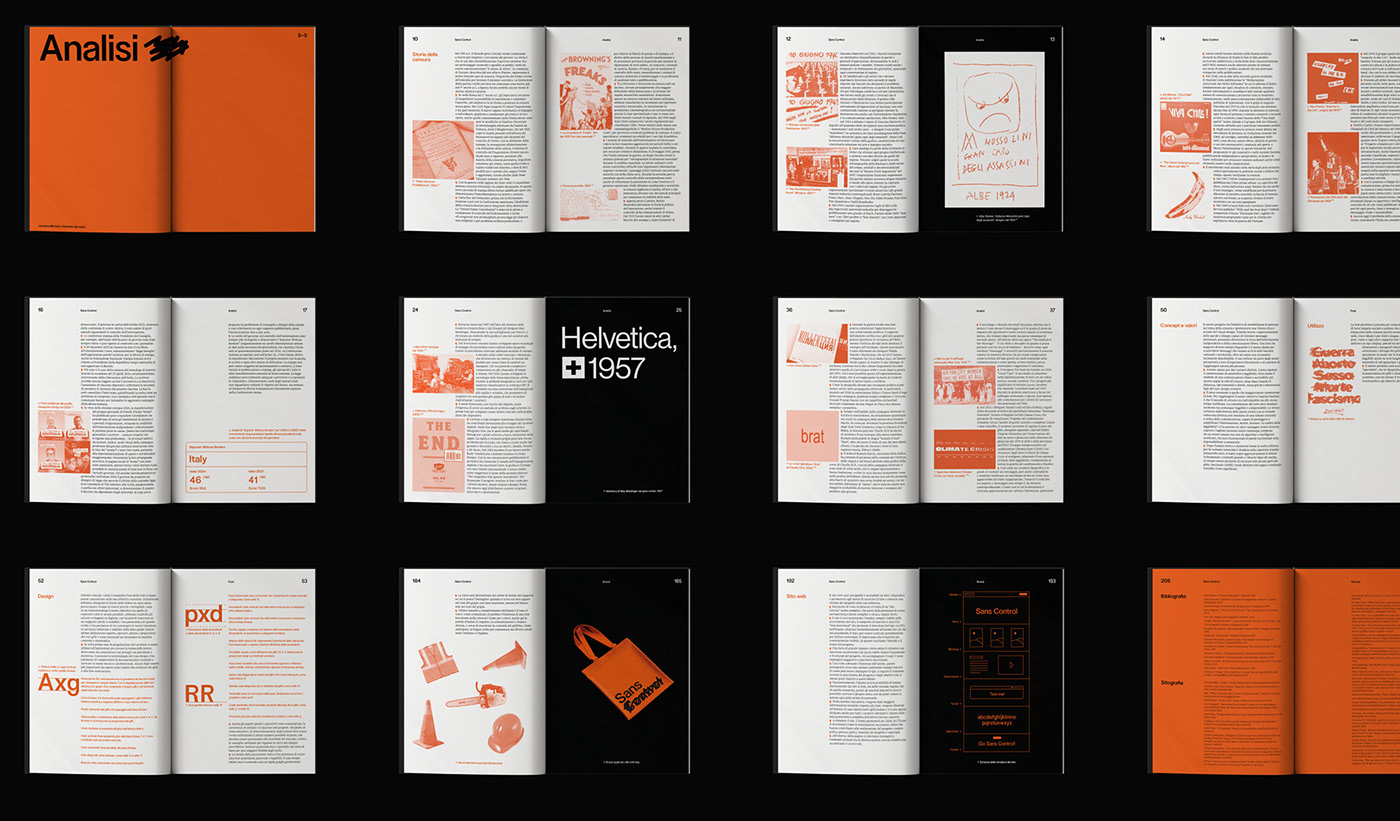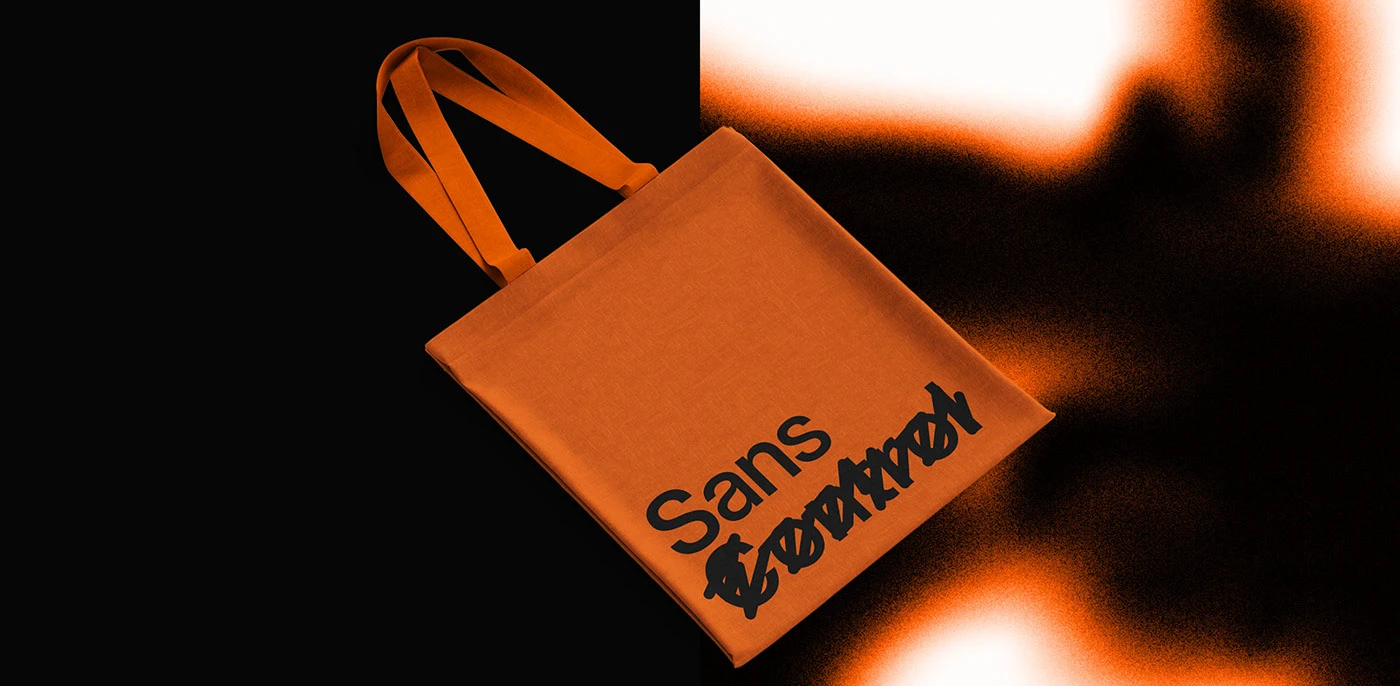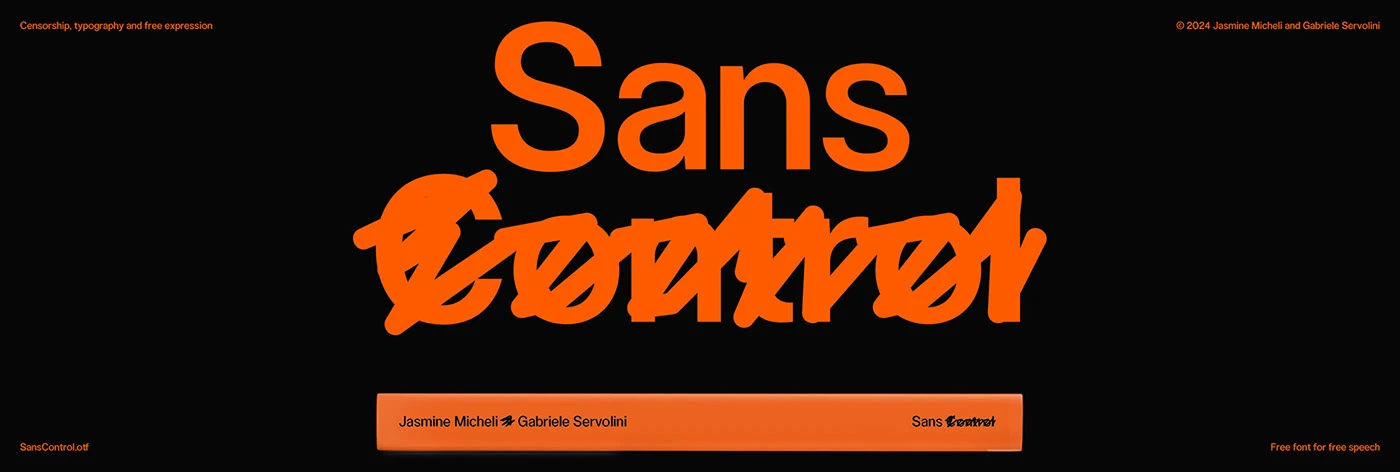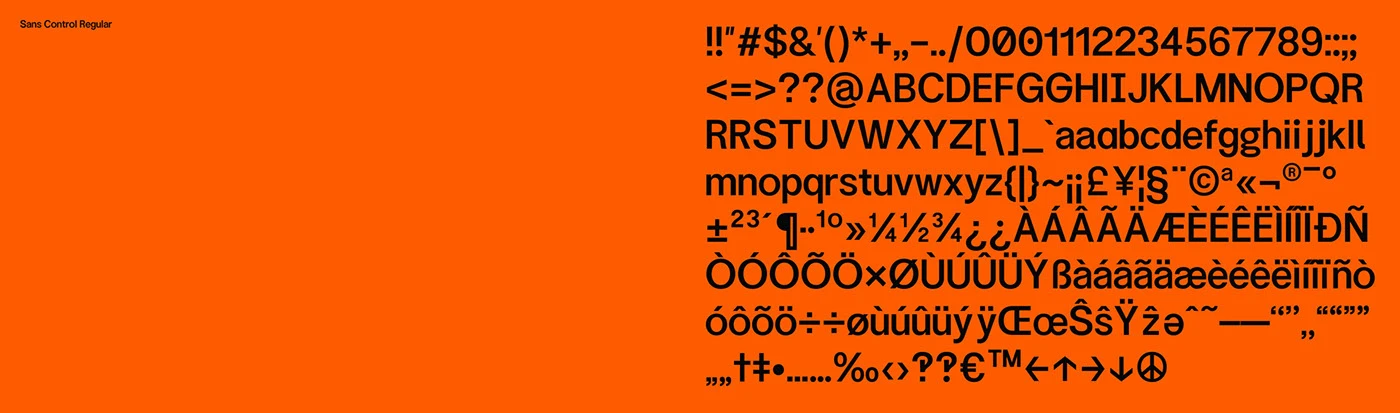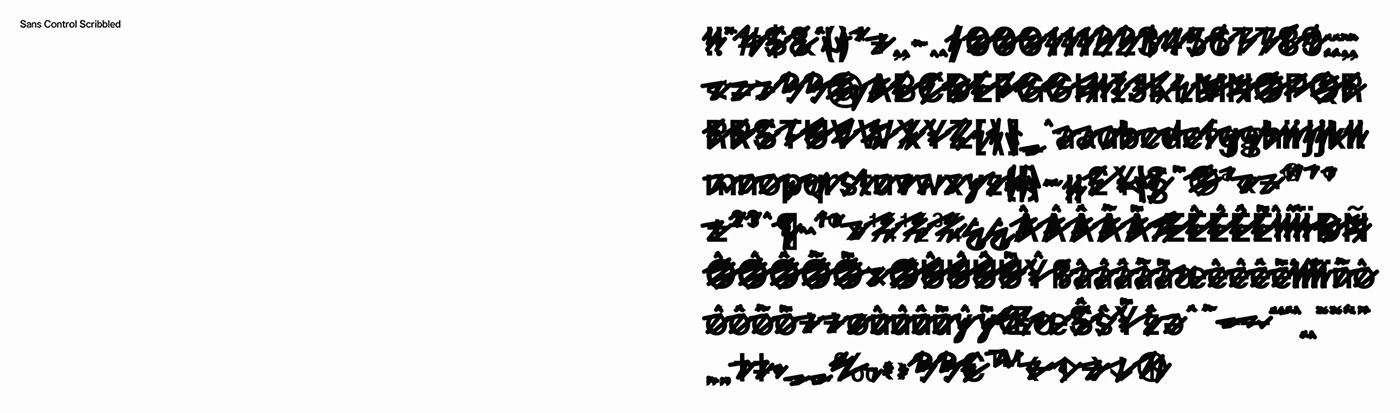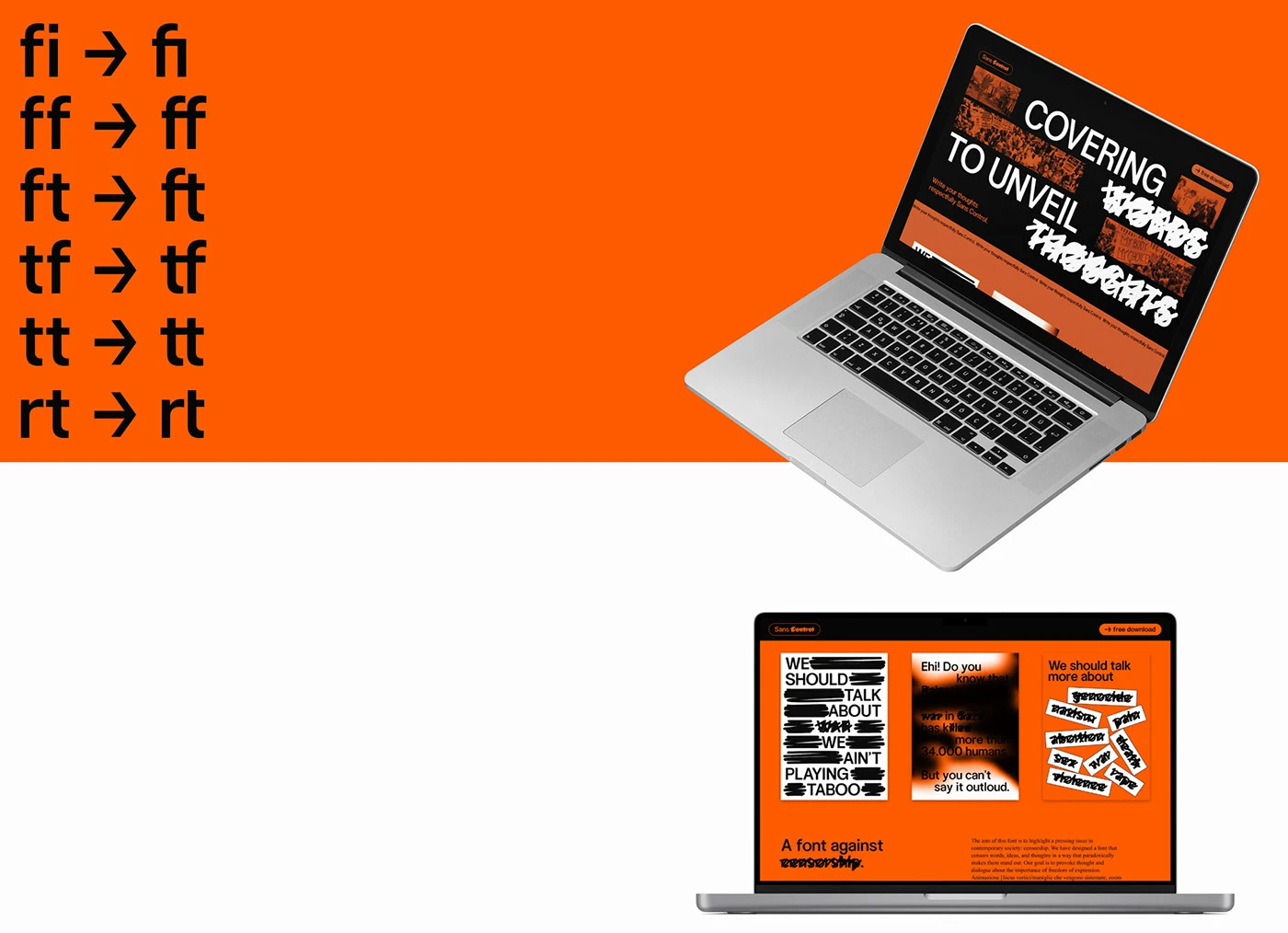
Bộ đôi nhà thiết kế Gabriele Servolini và Jasmine Micheli vừa làm mới lại các asset font sans-serif kinh điển, tạo nên một bản sắc thị giác cực kỳ ấn tượng và dễ nhớ. Bộ font miễn phí mới này sở hữu các nét dày dặn, đậm chất hình học (geometric) kết hợp cùng cấu trúc layout gọn gàng, mang đến một làn gió mới đầy hiện đại cho phong cách industrial (công nghiệp). Nhờ sự kết hợp khéo léo giữa hệ thống typography hiện đại và các biểu tượng tùy chỉnh, bộ font này trông vẫn rất gần gũi và dễ tiếp cận. Từng yếu tố nhỏ trong thiết kế đều cân bằng hoàn hảo giữa sự đơn giản về cấu trúc và cá tính năng động. Những ký tự được nâng cấp mang đến một góc nhìn đương đại cho các biểu tượng trực quan cổ điển, vừa sắc sảo, chính xác lại vừa ấm áp, đúng gu mà các designer ngày nay đang tìm kiếm.
Không chỉ gói gọn trong không gian kỹ thuật số, bộ font miễn phí này còn cực kỳ đa năng khi ứng dụng vào thực tế như in ấn poster, thời trang và bao bì tùy chỉnh. Những sản phẩm vật lý này đều giữ nguyên được bản sắc thiết kế sạch sẽ, giúp kết nối mạnh mẽ với cộng đồng designer ưa chuộng sự chỉn chu. Phong cách trực quan này là sự hòa quyện giữa layout trang đơn giản và hình ảnh sản phẩm sắc nét. Các hình khối modular tinh giản cùng độ dày nét đồng đều giúp tối ưu hóa trải nghiệm trên giao diện digital, tạo nên một phong cách đồng bộ và tăng độ uy tín cho thương hiệu trong ngành thiết kế.
Sau cùng, bộ font mới này giúp đơn giản hóa cách khách hàng tương tác với bộ nhận diện thương hiệu của doanh nghiệp. Các nhà thiết kế đã thành công trong việc tạo ra một trải nghiệm vừa thân thiện vừa cao cấp. Cấu trúc layout rõ ràng giúp người xem dễ dàng nắm bắt các chi tiết phức tạp chỉ trong nháy mắt, biến kho dữ liệu này thành một công cụ cực kỳ hữu ích cho những người bận rộn. Đây là minh chứng rõ ràng cho thấy thiết kế chiến lược có thể định hình lại thương hiệu doanh nghiệp một cách mạnh mẽ, tạo ra một công cụ đáng tin cậy, kết nối tốt với người dùng và khẳng định vị thế vững chắc trên thị trường. Xem thêm thông tin chi tiết tại www.behance.net/gallery/218476347/Sans-Control-Free-Font.
Design duo Gabriele Servolini and Jasmine Micheli just gave classic sans-serif font assets a serious upgrade, delivering a visual identity that’s incredibly striking and unforgettable. This new free font features bold, geometric strokes paired with a clean, structured layout, breathing fresh, modern life into the classic industrial style. By cleverly blending modern typography with custom symbols, the typeface remains totally approachable and friendly. Every little detail perfectly balances structural simplicity with a dynamic personality. These upgraded characters offer a contemporary spin on classic visual icons—sharp, precise, yet warm, hitting the exact sweet spot for today’s designers.
Far from being confined to digital screens, this free font is incredibly versatile in the real world, shining across printed posters, fashion items, and custom packaging. These physical pieces maintain that clean design vibe, creating a strong connection with designers who appreciate pure precision. The visual style seamlessly blends straightforward page layouts with crisp product photography. Minimalist modular shapes and consistent stroke weights optimize the digital interface experience, building a cohesive look and boosting brand credibility in the design world.
Ultimately, this new font streamlines the way clients interact with a company’s brand identity. The designers nailed it by crafting an experience that feels both friendly and high-end. The clear layout lets viewers catch intricate details in a flash, making this asset an incredibly handy tool for busy professionals. It’s a prime example of how strategic design can powerfully reshape a corporate brand, providing a reliable tool that connects with users and secures a strong market presence. Check out all the details over on www.behance.net/gallery/218476347/Sans-Control-Free-Font.